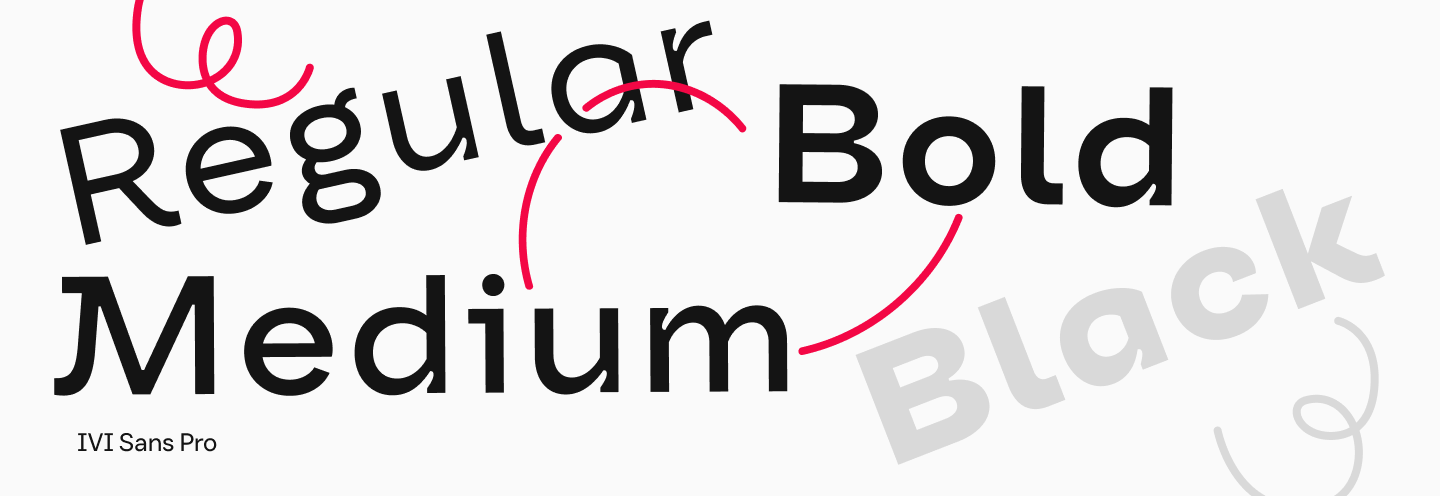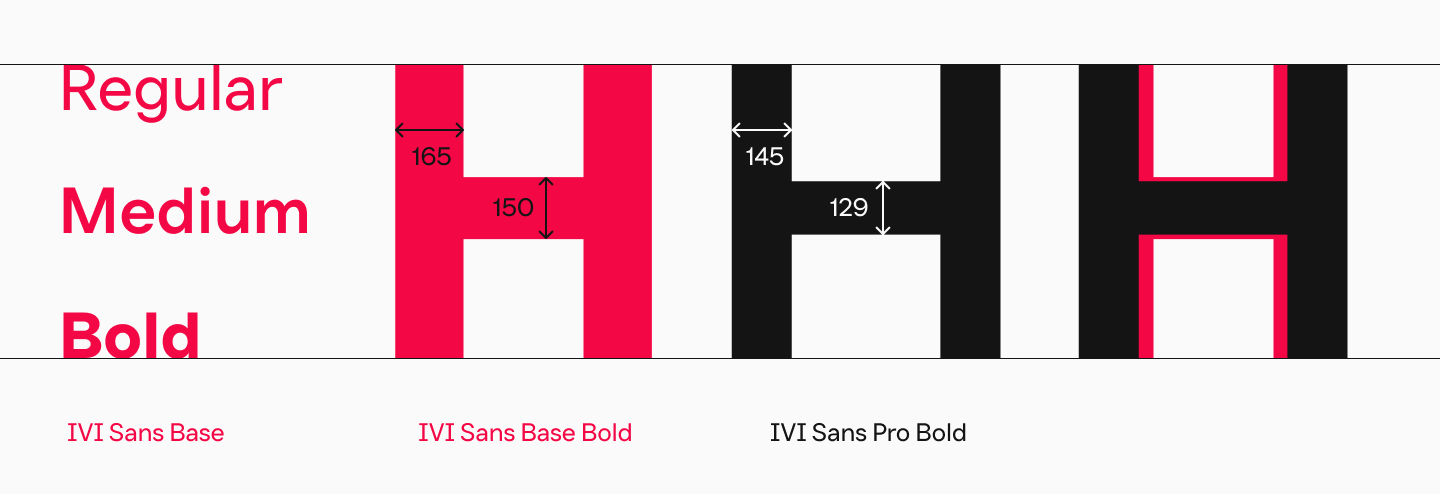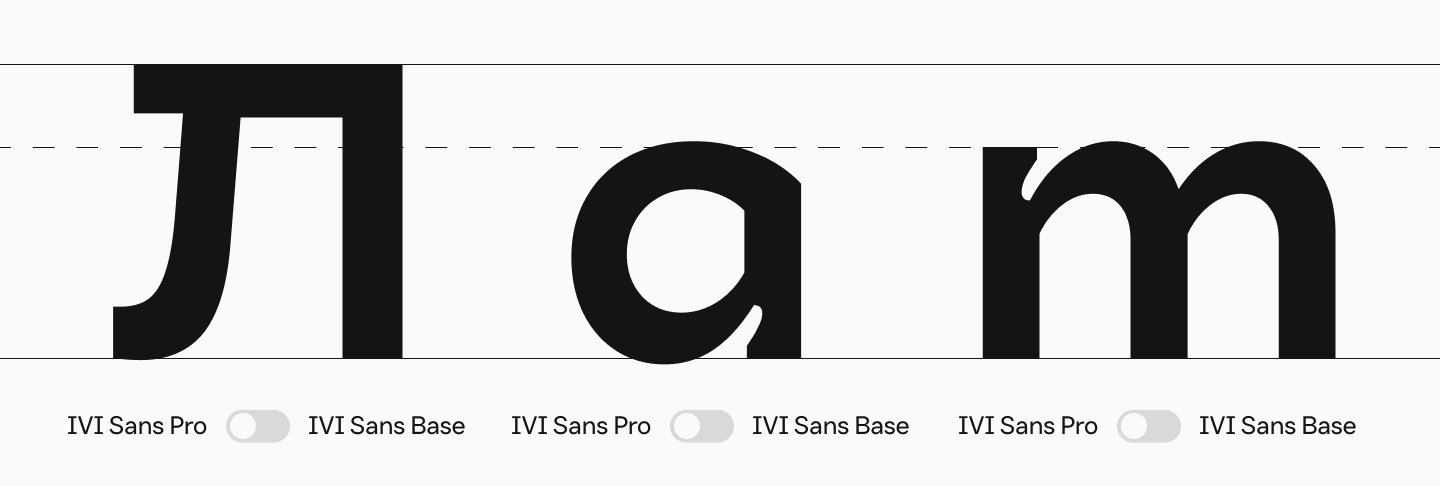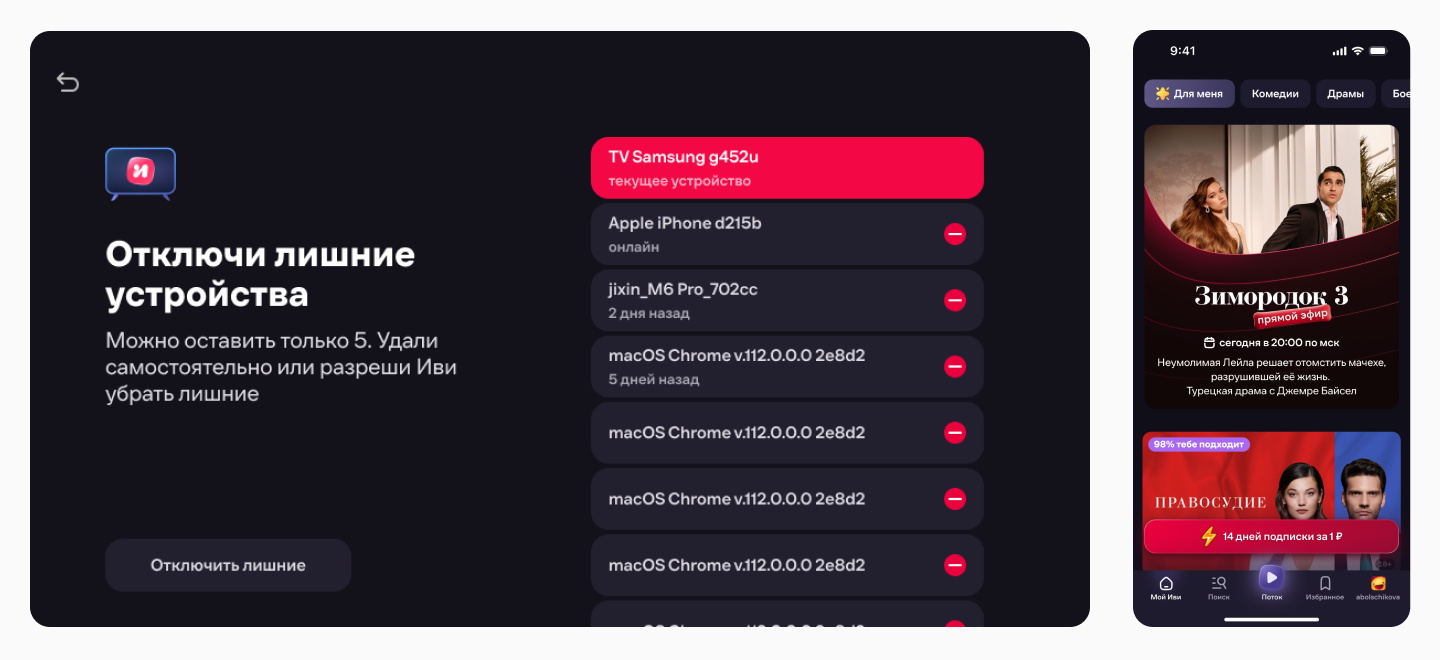
Часть 1: новая задача
Напомним, что в 2022 году у Иви произошел ребрендинг: айдентика стала более мягкой и дружелюбной, на смену острым углам в логотипе пришли скруглённые формы, а позже мы разработали соответствующий новому характеру бренда фирменный шрифт — Ivi Sans Display. Он выполняет функции дисплейного и используется в коммуникациях бренда: в соцсетях, рекламе, афишах, ТВ-роликах и так далее.
А вот интерфейсный (или текстовый) шрифт оставался прежним, пока образ бренда продолжал меняться и совершенствоваться. И в конце концов команда Иви решила, что пора обновить всю типографику, ведь это важный элемент айдентики.
Существующий шрифт не очень хорошо подходил к созданному нами ранее дисплейному шрифту и не подчёркивал характер бренда.
Кроме того, он был шире, чем стандартные интерфейсные шрифты, и это создавало ряд неудобств.
Так, у нас появилось три критерия, которым должен был соответствовать новый интерфейсный шрифт:
- Информационная плотность: нужно сделать новый шрифт более узким, чтобы в строку текста входило большее количество символов;
- Брендовость: коммуникационная ценность и узнаваемость должна быть выше, чем у текущего шрифта;
- Читабельность: важно, чтобы шрифт при этом не стал более нагруженным и считывался всё так же быстро и легко.
Опираясь на эти пункты, мы начали искать пути реализации проекта.
Часть 2: поиск решений
Первоначально у нас было два пути: сделать кастомизацию Ivi Sans Display или одного из шрифтов TypeType. В итоге выбрали второй вариант и развивали идеи в этом направлении. Соответственно, у нас была задача кастомизировать шрифт так, чтобы добавить в него брендовую составляющую, но при этом сохранить читабельность и сделать его более узким, чем текущий шрифт.
Совместно с командой Иви мы выбирали вариант из подходящих для этой цели шрифтов.
Поэтому мы вернулись к самому первому пути — кастомизировать Ivi Sans Display, упростив его формы. А для того, чтобы лучше понять, в какую сторону двигаться и найти баланс между читабельностью и брендинговой составляющей, тщательно изучили самые известные интерфейсные шрифты — San Francisco Text, Roboto и другие. Мы смотрели на их формы, пропорции, апроши и другие детали.
Выяснилось, что в основном среди интерфейсных шрифтов встречаются неогротески, у которых сквадраченные овалы и вытянутые пропорции. Однако у Roboto довольно плотные апроши, а у San Francisco, наоборот, очень свободные. С учётом наших задач мы решили двигаться в сторону Roboto.
После этого началась работа над семейством. Мы определяли, какие начертания должны быть в шрифте. У Ivi Sans Display четыре начертания — Regular, Medium, Bold, Black. А в интерфейсе дизайнеры Иви используют только три начертания — Regular, Medium, Bold. У них уже есть готовая структура и представление о том, какие начертания в каких макетах используются. Поэтому совместно с командой Иви мы решили, что четвертое начертание, то есть Black, в шрифте будет лишним, потому что они его не используют и использовать не планируют.
Также мы думали над тем, чтобы сделать начертание Light — чтобы понять, нужно ли оно, дали команде Иви протестировать его в наших шрифтах. Но, как оказалось, оно тоже не требуется.
Соответственно, план был следующий: сделать три начертания — Regular, Medium и Bold. При этом жирность в Bold должна быть чуть больше, чем в Ivi Sans Display, а в Regular примерно такая же, как в дисплейном шрифте.
Часть 3: реализация
Мы приступили к переработке Ivi Sans Display. Чтобы сделать его менее декоративным и более читабельным, в первую очередь нужно было упростить формы знаков.
Так, мы убрали большую часть асимметричных терминалов (впрочем, некоторые оставили для придания характерности). Полностью убрали ловушки для чернил, чтобы они не мешали читабельности в маленьком размере. Убрали курсивные формы в кириллице, так они могут быть непривычны и неудобны для быстрого чтения. Упростили декоративные формы — например, сделали одночастную «а» двухчастной. Также упростили формы «Л», «М» и других букв — убрали «крышечки» и другие детали.
Однако, убрав большую часть декоративных фишек, мы столкнулись с очередным нюансом. Дело в том, что начертание Bold текстового шрифта часто используется в макетах в довольно крупном размере — например, в акцентных или призывающих к действию надписях. А значит, в нём должна сохраниться брендовая составляющая и характерные детали, нейтральный шрифт для таких целей не подойдёт.
В рамках «прогрессии декоративности» в начертании Bold меняются и другие символы: например, у цифр появляются терминалы, меняются формы запятой и знаки на её основе — они почти такие же, как в Ivi Sans Display, но немного упрощённые. Служебные знаки также везде упрощаются, чтобы шрифт был проще для восприятия.
Во всех начертаниях так же, как в Ivi Sans Display, поднимаются все символы пунктуации между цифрами (точки, двоеточия и другие). Ведь в интерфейсах Иви часто используются таймкоды, даты и тому подобное.